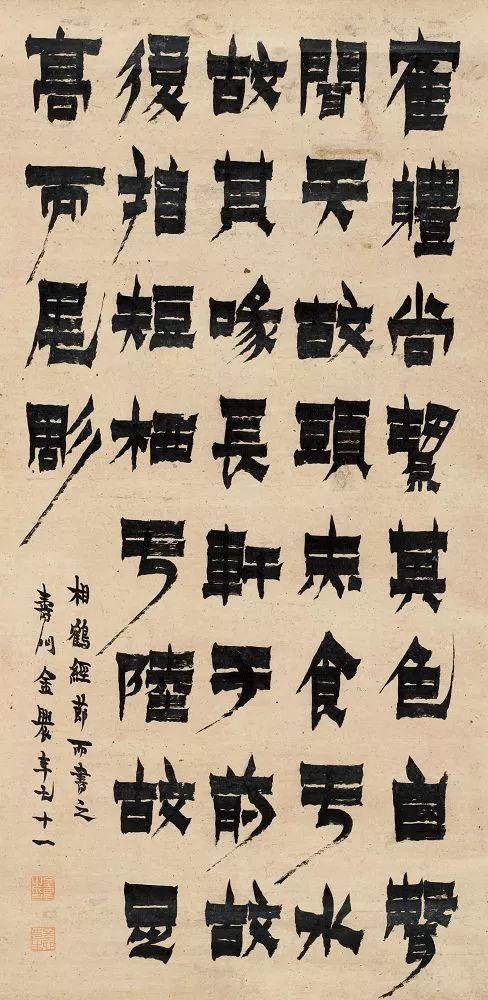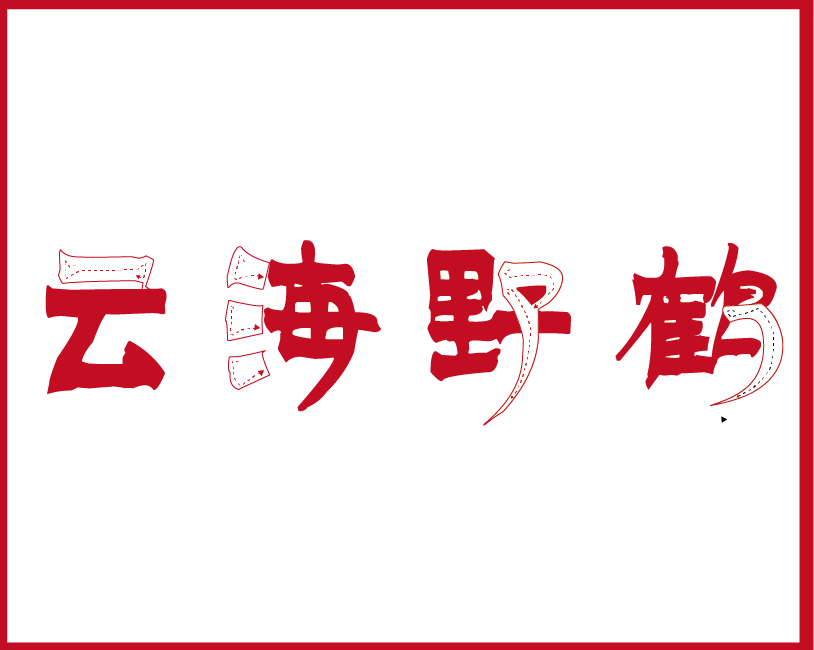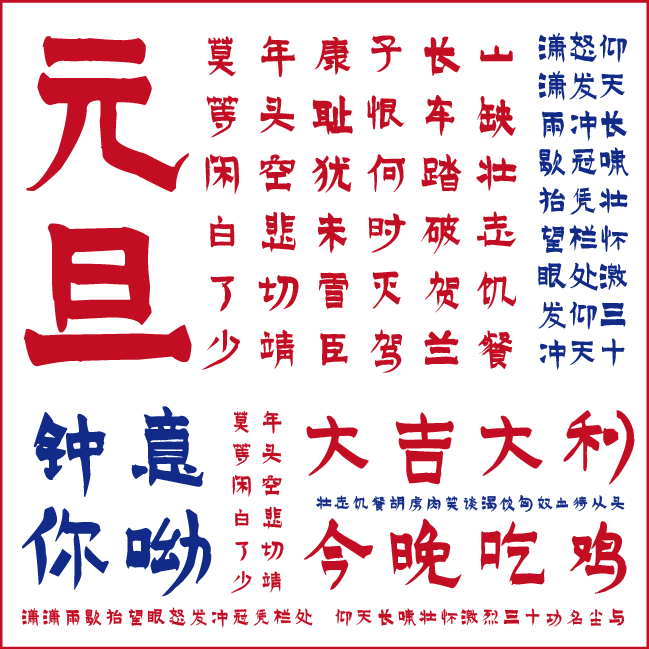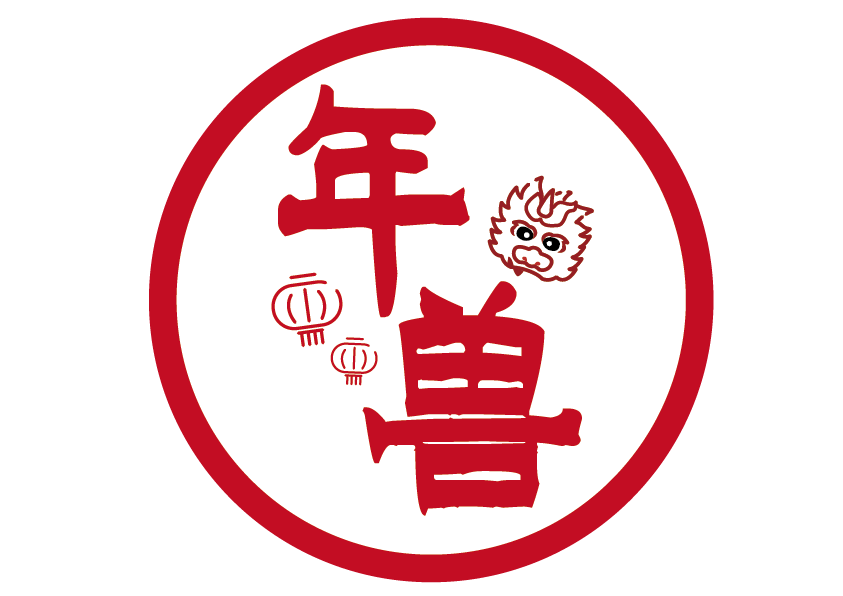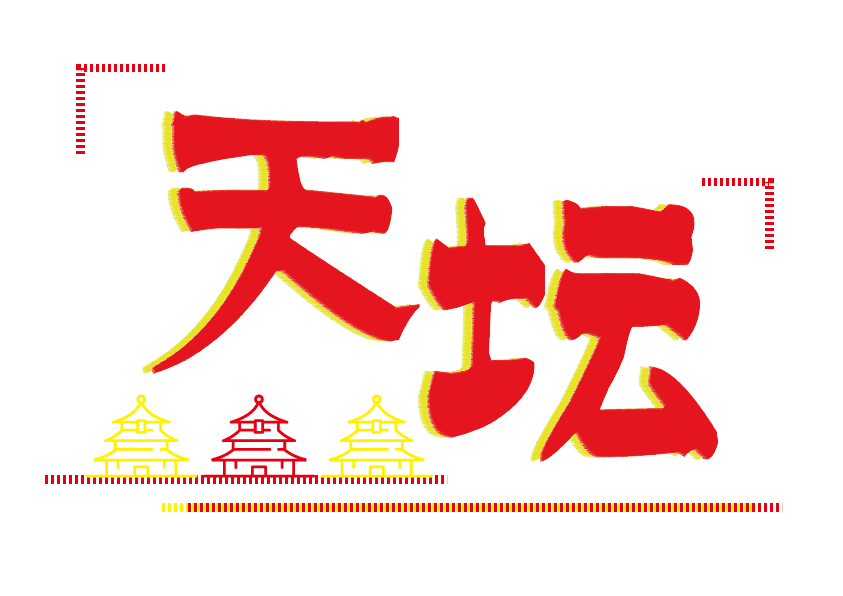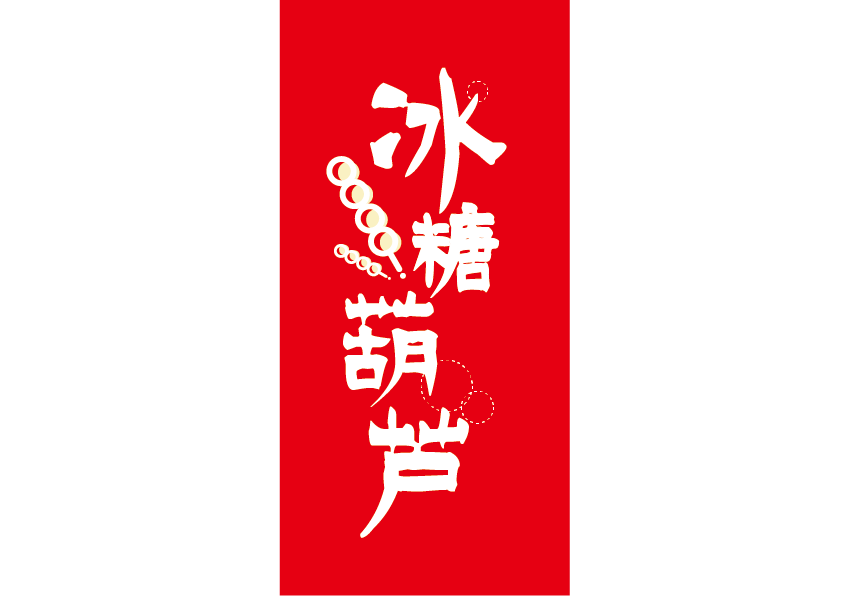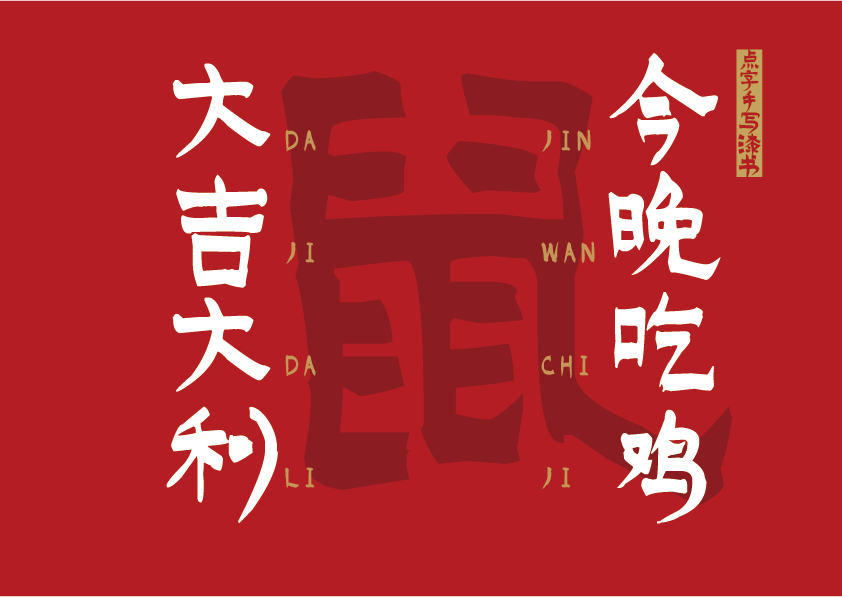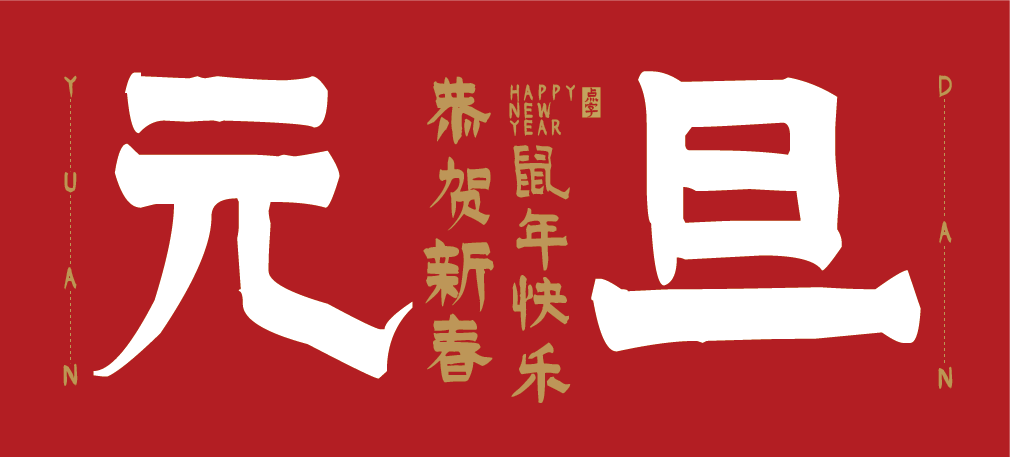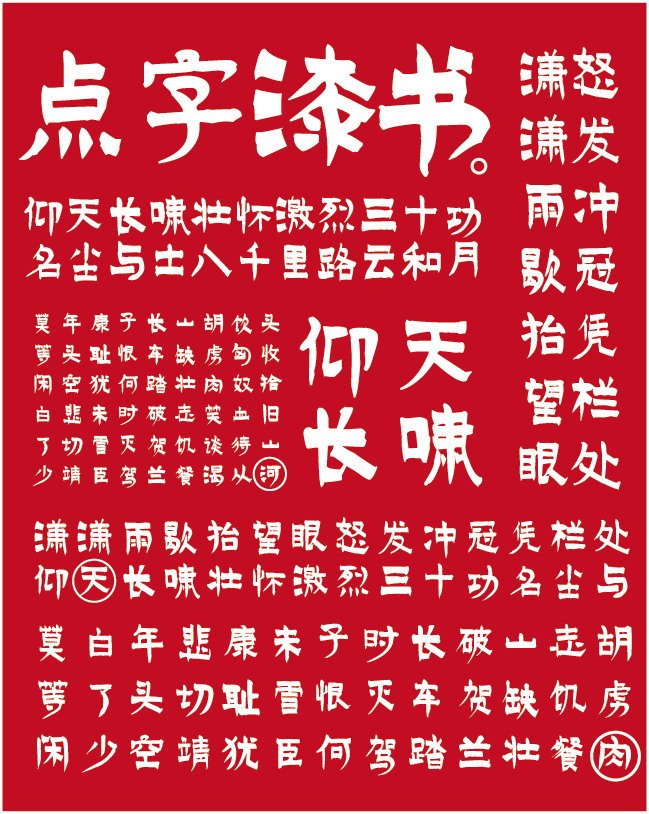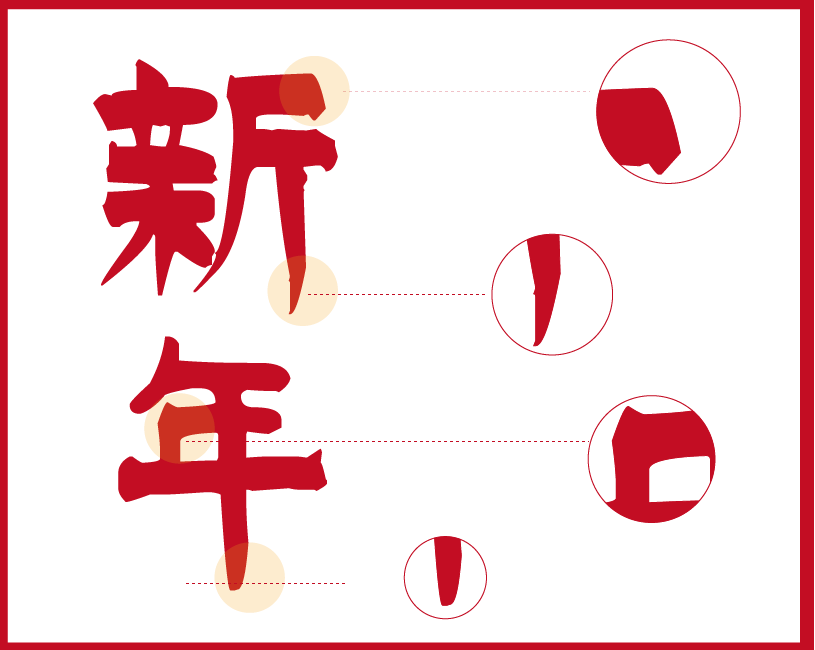
看到上面的字型对书法不太了解的朋友一定会较为陌生,它便是清代书画名家金农所创字型,将汉隶与魏碑二者风格融为一体,墨色乌黑光亮宛如漆成。被世人称为——漆书
点字手写漆书充分吸收金农漆书风格特点:笔画方正、棱角分明,横画粗重而竖画纤细。
点字手写漆书风格规整,结构严谨。高度还原了金农漆书的书法韵味,如此风格迥异且气势磅礴的字体用在今晚的跨年之夜相信在合适不过了。